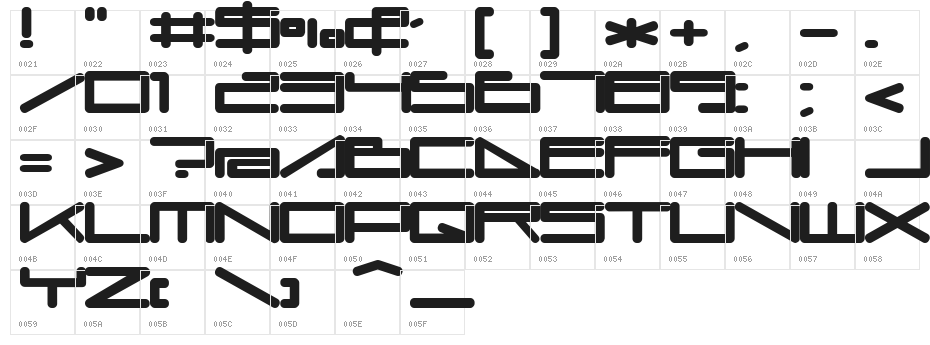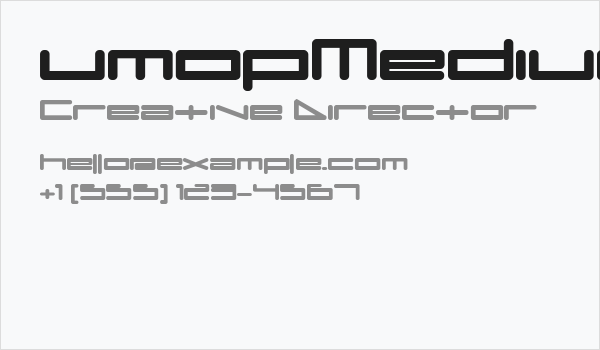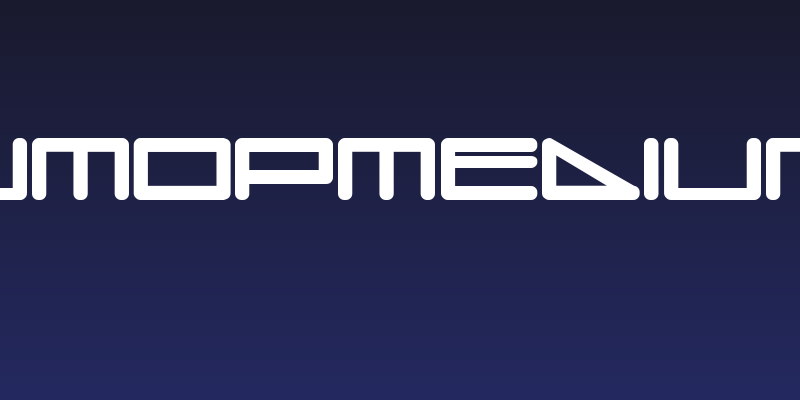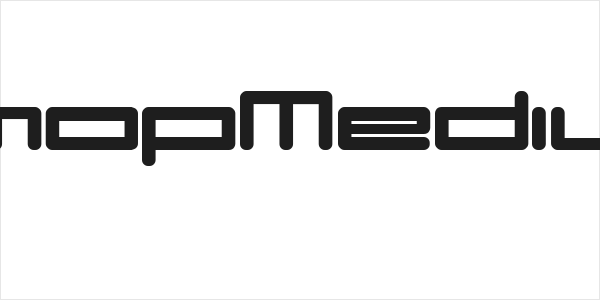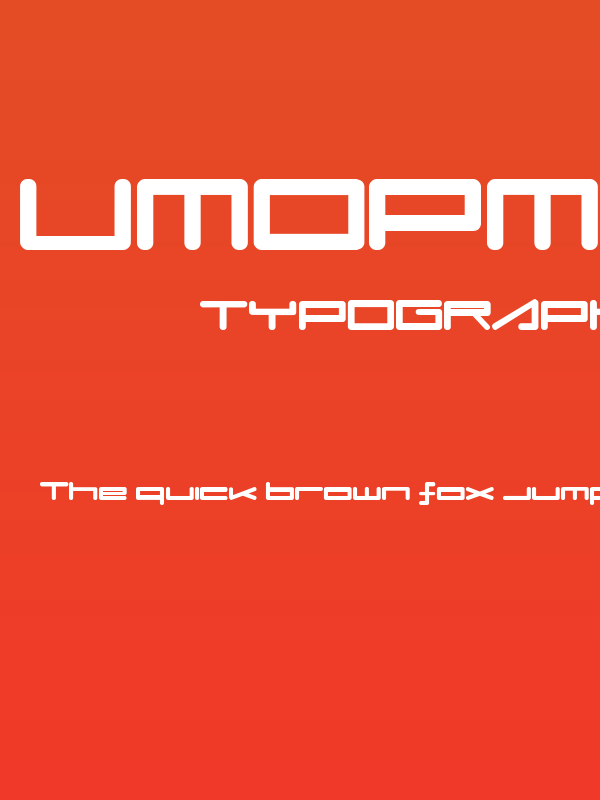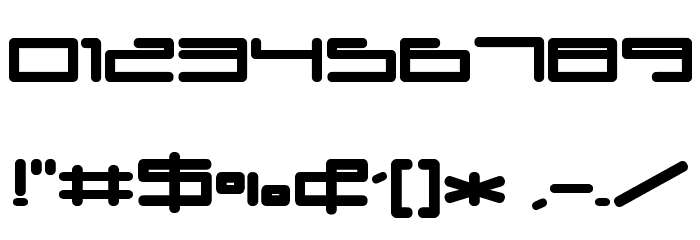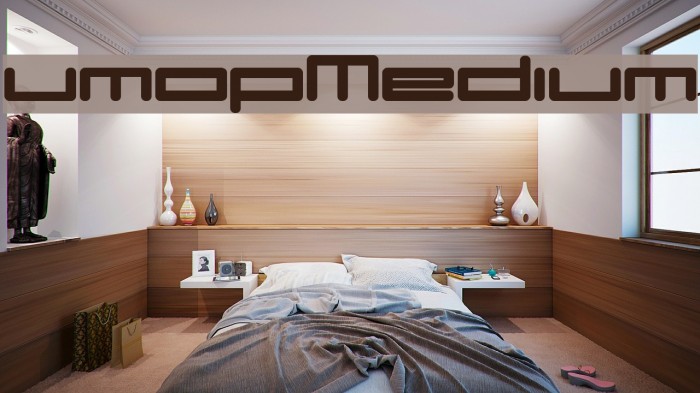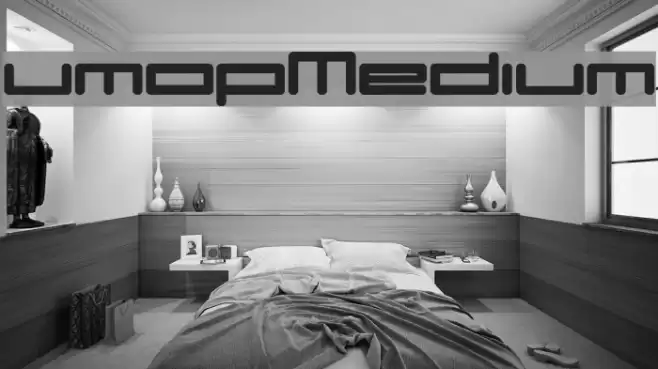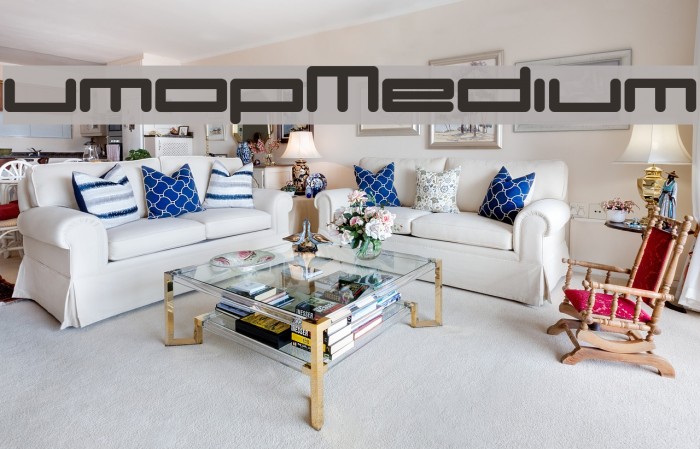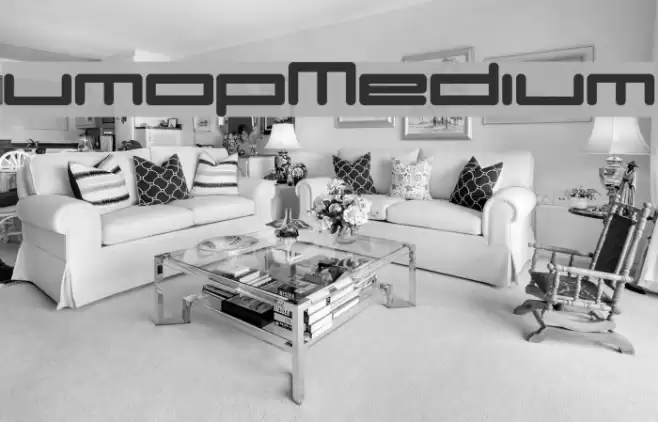
umopMedium Font
UMOPMEDIUM MAIUSCOLE
UMOPMEDIUM MINUSCOLO
UMOPMEDIUM ALTRI CARATTERI
| Progetti proposti | Ideal for technology branding, sci-fi themed designs, video game interfaces, and modern advertising campaigns. |